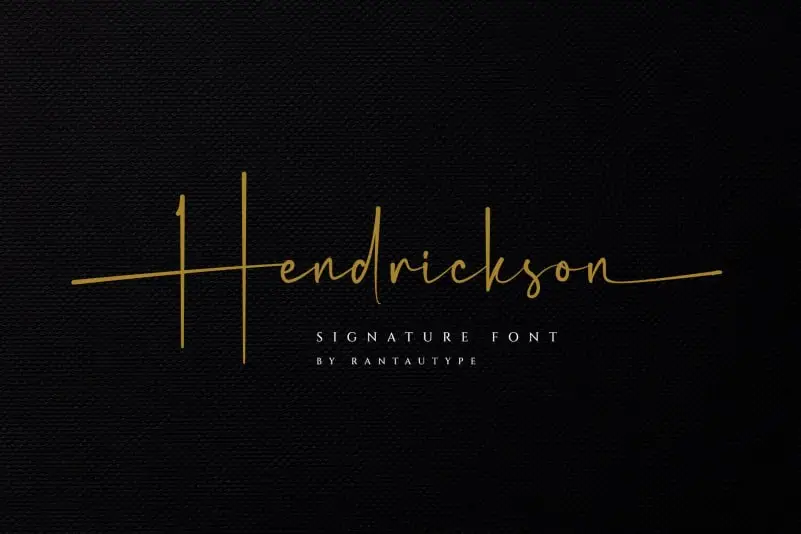
Hendrickson Script Font – Download Grátis
A fonte Hendrickson Script é inspirada no charme de uma assinatura que torna a escrita única e interessante. Esta fonte é criada e compartilhada pelo designer Rantautype, e ela se destaca por sua elegância, sofisticação, premiumidade, modernidade, leitura fácil e estilo sedutor, especialmente adequada para design de cartaz, capas de livros, revistas, business cards e projetos de design em geral. Suave como uma assinatura, Hendrickson é a escolha perfeita para o rótulo de água-moleque em fotografias ou para as assinaturas dos logotipos de empresas. Sem dúvida, ela transforma seu trabalho nos níveis mais altos!